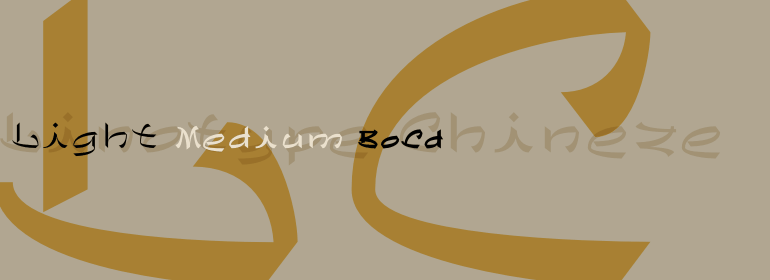
Linotype Chineze™
Linotype Chineze™,这款字体结构工整、笔画清晰,兼顾美观与易读性,适用于标题、正文、海报、包装、LOGO 等多种场景。字形优雅稳定,风格百搭耐看,适配日常排版与创意设计,让文字呈现更舒适、更具质感。Linotype Chineze™一笔一画,皆是细节,以均衡的比例、流畅的线条打造舒适视觉体验,字形端正大气,风格简约现代。无论是商业设计、品牌宣传还是日常排版,都能轻松驾驭,让文字更有格调与力量。Linotype Chineze™字体下载。
2002年,德国设计师Peter Huschka创作了Linotype Chineze,一种类似于汉字书法笔触的字体家族。Linotype Chineze使用各种像笔刷一样的元素,使罗马字母充满了东方风格。在菜单、漫画书或者食品包装上试试这款字体!喜欢这种异国情怀吗?那就试试看来自Huschka的另外两款东方风格的字体家族Sinah和Sinah Sans。
The German designer Peter Huschka created Linotype Chineze, a family of typefaces that resemble the calligraphic strokes found in Chinese characters, in 2002. Using a variety of brush-like elements, Linotype Chinese imbues the Roman alphabet with an Eastern flair. Try out this font in a menu, a comic book, or on food packaging! Like this foreign feeling? Check out Sinah and Sinah Sans, two other Eastern-inspired font families from Huschka."